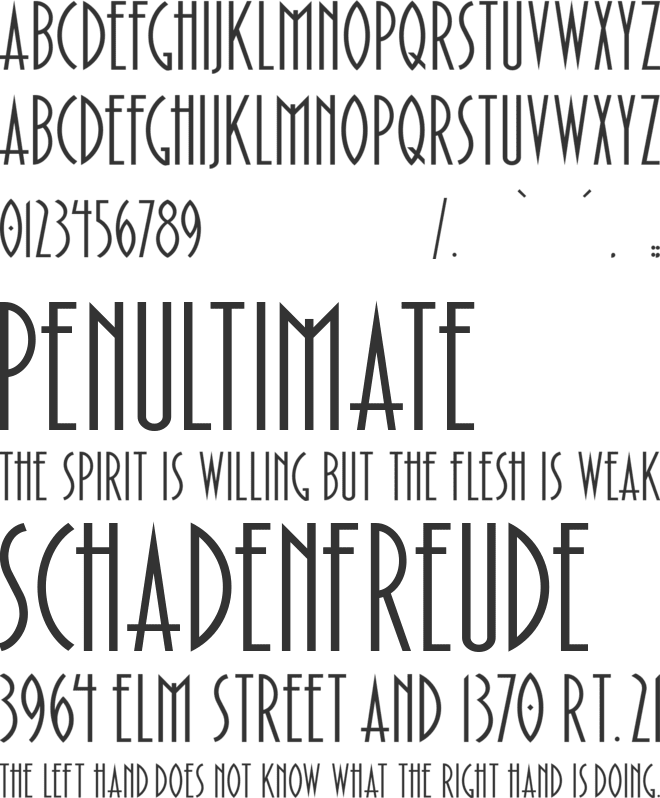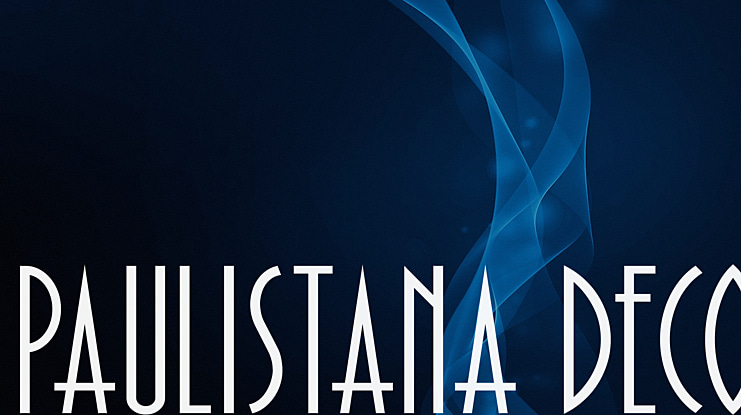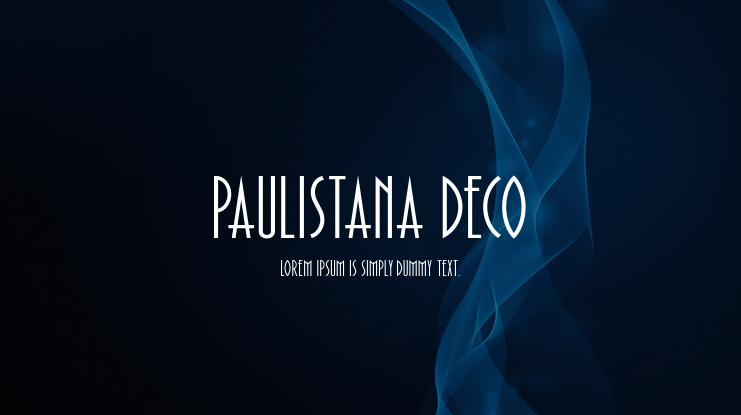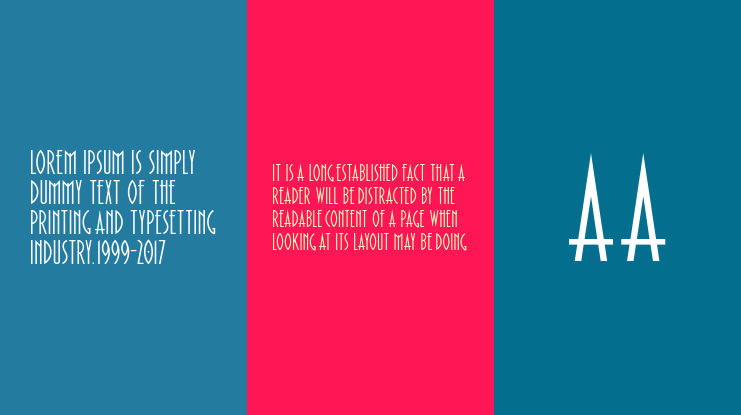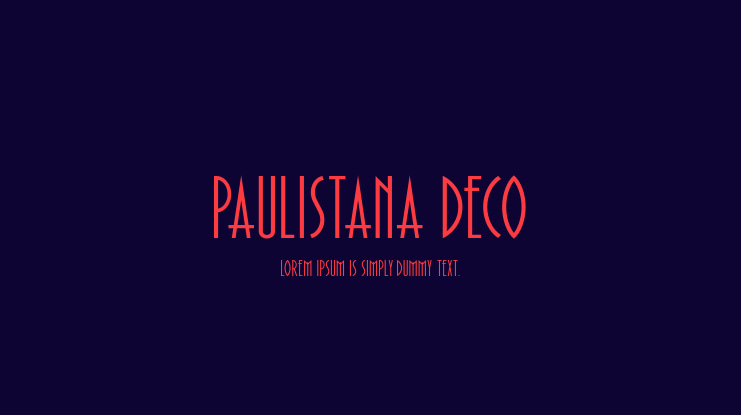
Paulistana Deco Font
Sergio Salgado
Série Paulistana – Pesquisa sobre a tipografia na arquitetura da cidade de São Paulo (Brasil).
Paulistana Series - Research about the typography in the architecture of the São Paulo city (Brazil).